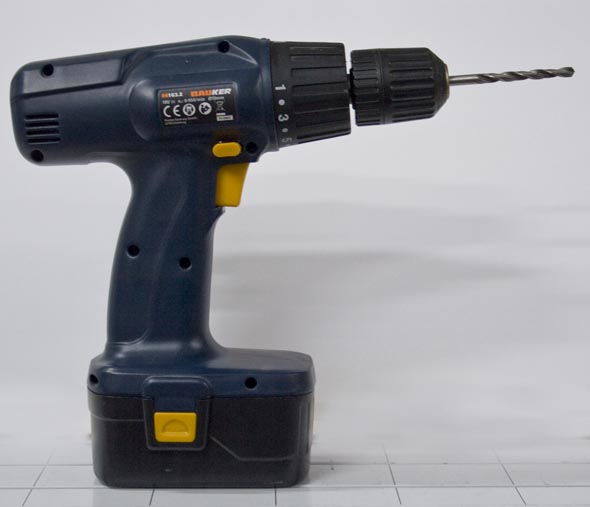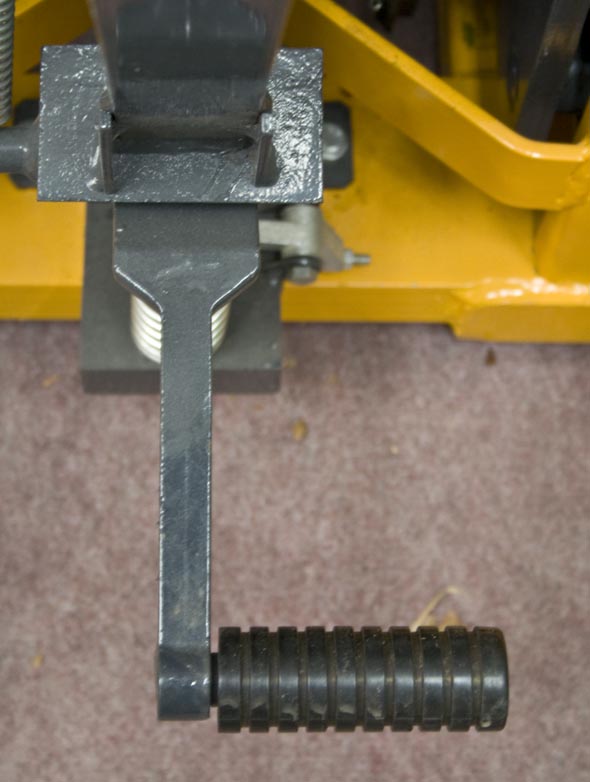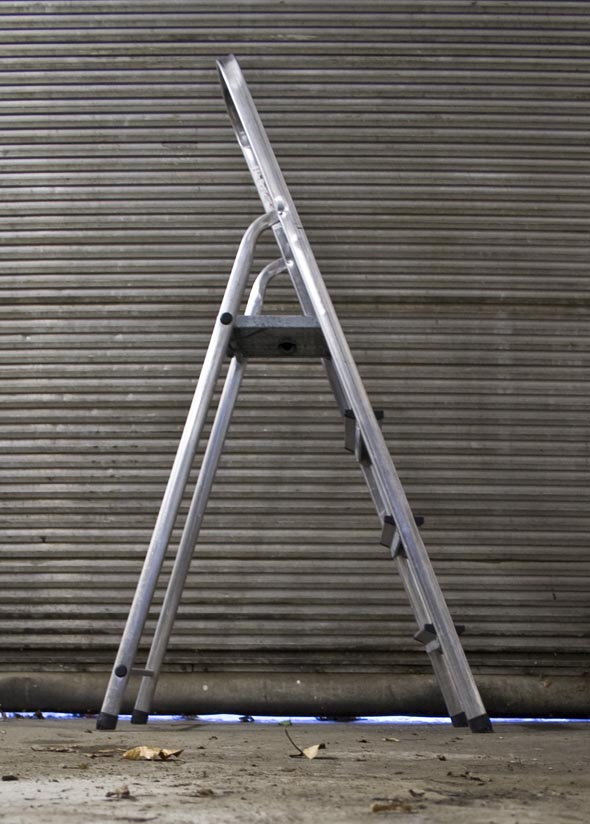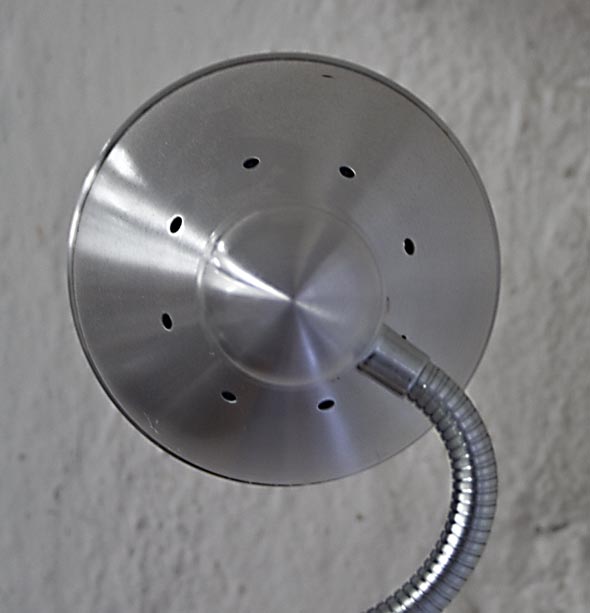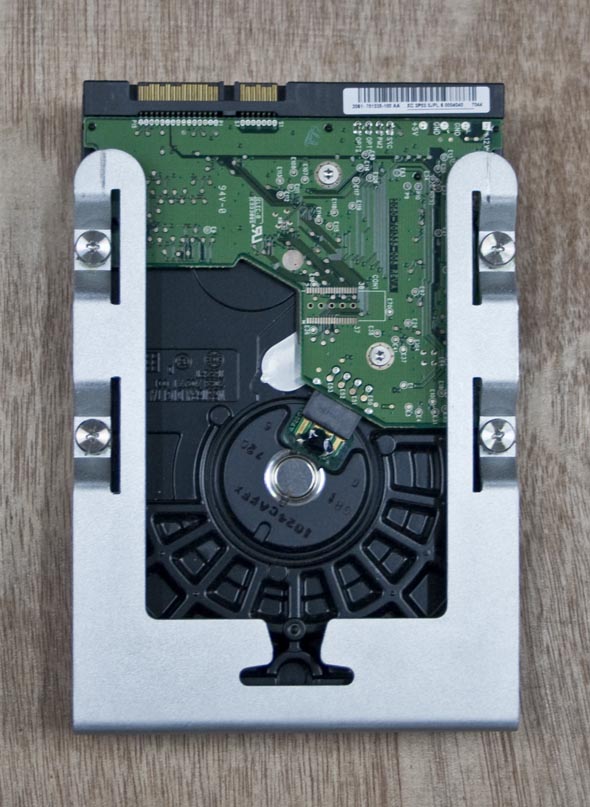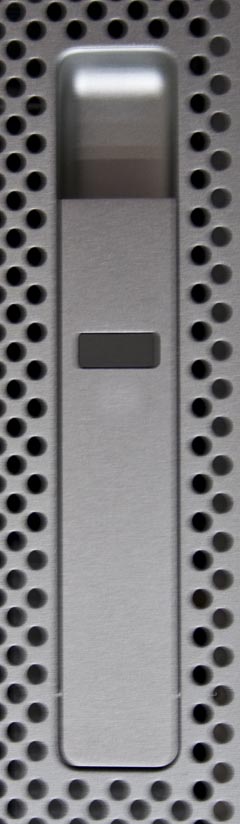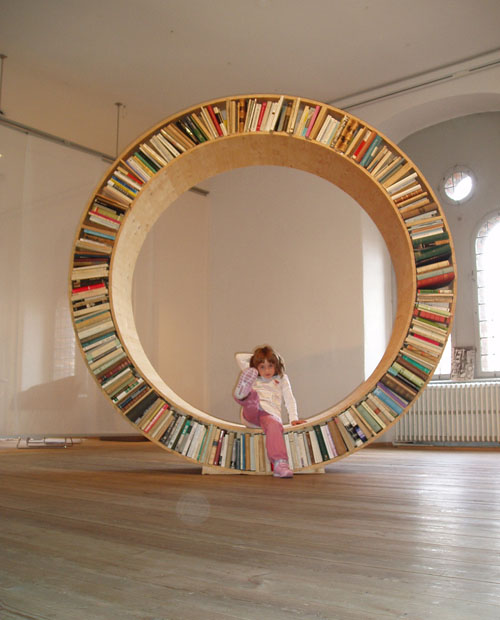
Buchstaben entdecken
die Weihnachtsjobs sind hoffentlich alle erledigt und so langsam kehrt ein klitzekleines bisschen Ruhe in den Arbeitsalltag ein. Der Umzug ins neue Forumszuhause ist geglückt, nur wenig zu Bruch gegangen und die Kartons sind weitgehend ausgepackt und eingeräumt. Bis auf das Versaleszett sind auch schon alle Buchstaben wieder an ihrem Platz … ;-)
Es wird also höchste Zeit, mal wieder ein bisschen was zu spielen, oder? Aus diesem Grund dieser niegelnagelneue Thread. Hier sind die …
… Spielregeln:
Gesucht werden Fotos von Buchstaben, die sich zufällig und ohne unser Zutun im architektonischen Stadtbild ergeben. Also keine echten Buchstaben im Sinne von Werbebannern oder Logos sondern architektonische Strukturen, die zufällig die Form eines Buchstabens ergeben. Ziel ist es, gemeinsam ein vollständiges Alphabet zusammenzubekommen. Erlaubt sind Groß- und Kleinbuchstaben, lang-s und ß natürlich auch. Und wer Satzzeichen entdeckt – die werden selbstverständlich ebenfalls gerne genommen.
Es ging mir um die Struktur im Pylon, das ist ein X. Aber Du hast recht, ich liefere noch mal einen eindeutigeren Ausschnitt …
Sehr cool, extra für Dich machen wir die Sonder-Indoor-Kategorie »Haushalt und Werkstatt« auf, ok?
Und nichtlateinische Alphabete bitte auch.
(Die Regel, die da irgendwas von »architektonischem Stadtbild« sagt, habe ich erst hinterher gelesen und hatte keine Lust, den Post wieder zu löschen. Aber vielleicht kann man das insgesamt liberaler handhaben.)
Also wie gesagt – Du hast feierlich eine neue Unterkategorie bekommen, ist doch super! ;-)
Nichtlateinische Alphabete? Hmmm, da bin ich ja mal sehr gespannt, was Du da anschleppst. ;-)
Wenn Du Deinen Blick nach oben schweifen läßt, siehst Du, daß ich mit dem Lambda schon den Anfang gemacht habe. Den Rest hellenischer Buchstaben habe ich für die anderen übriggelassen, die wollen ja auch noch was zu posten haben.
Na, da mußt Du eben Google Earth bemühen und so lange suchen bis Du es findest! Und wenn Du schon dabei bist kannst Du Dich auch gleich um Umlaute kümmern! hoerthoert.gif
Wenn Du Deinen Blick nach oben schweifen läßt, siehst Du, daß ich mit dem Lambda schon den Anfang gemacht habe. Den Rest hellenischer Buchstaben habe ich für die anderen übriggelassen, die wollen ja auch noch was zu posten haben.
Ja, über das Lambda habe ich schon meinen bewundernden Blick schweifen lassen. In Ordnung, griechische Buchstaben darfst du auch sammeln, aber bei Persisch steige ich aus – das kann ich nicht beurteilen. Es sei denn, es meldet sich ein Sachverständiger für Auswärtsbuchstaben und hilft mir … :-?
Na, da mußt Du eben Google Earth bemühen und so lange suchen bis Du es findest! Und wenn Du schon dabei bist kannst Du Dich auch gleich um Umlaute kümmern! hoerthoert.gif
Ja und um das @ …
Oh schön, tolle Farben noch dazu! Sag bloß, so schöne Fotomotive gibt es in Frankfurt? ;-)
Das ist übrigens meine Qurze …:-P
Süß die Qurze – und großartig das Möbelstück!
Dein Q wird feierlich aufgenommen in der Rubrik »Indoor«
:-)
Sehr praktisch. Da kann die Qurze sich perspektivisch entscheiden zwischen einer mehr intellektuellen Laufbahn (Bücher) und einer mehr sportlichen (Rhönrad).